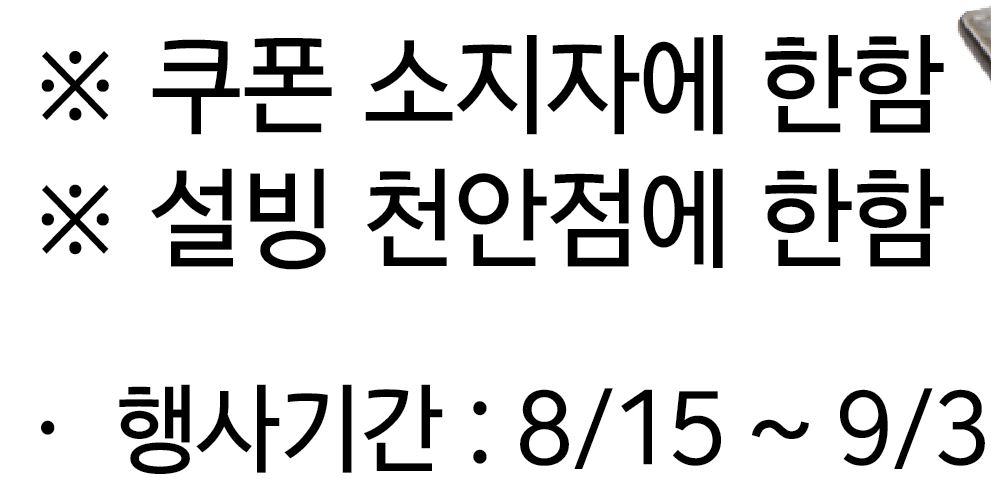
폰트좀 알려주시면 감사^^ 정보 폰트좀 알려주시면 감사^^ 개애비 자기소개 아이디로 검색 회원게시물 2015.08.12 19:00:48 조회 3,086 댓글 1 이전 게시글 다음 게시글 목록 본문 나눔고딕인줄 알앗는데. 아니네요.ㅠㅠ 요것어떤체인지 아시는분 부탁드립니다. 댓글 1개 naaman 자기소개 아이디로 검색 회원게시물 16.02.05 23:27:37 이거 이마트타운에서 쓰는 폰트던데... 댓글 설정 댓글 신고 이거 이마트타운에서 쓰는 폰트던데... 이전 게시글 다음 게시글 목록
naaman 자기소개 아이디로 검색 회원게시물 16.02.05 23:27:37 이거 이마트타운에서 쓰는 폰트던데... 댓글 설정 댓글 신고 이거 이마트타운에서 쓰는 폰트던데...